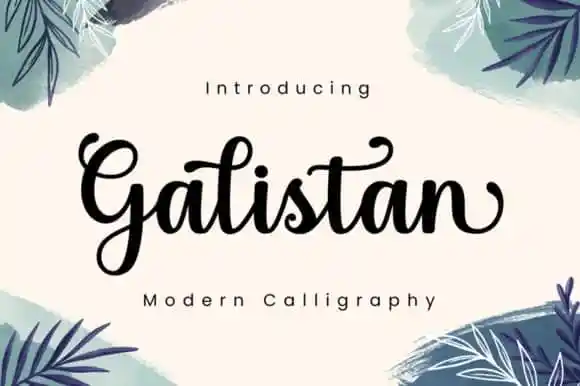
Galistan Calligraphy Font – Download Grátis
A Galistan Calligraphy Font é uma beleza que desperta a imaginação dos criativos. Ela foi feita com amor, trazendo designs até mais vivos e engraçados ainda. Seu equilíbrio de caracteres faz com que ela se adeque perfeitamente em um vasto conjunto de criações. Além disso, é particularmente encantadora para os designers apaixonados por stickers ou decalques. Adicione esses elementos ao seu mais criativo conceito e assista enquanto transformam suas ideias em realidade. Esta fonte vem para aquecer seus projetos com uma paleta única de cores e expressões únicas, tornando cada trabalho mais especial. Descubra por si mesmo o poder que esta font pode ter em seus designs!